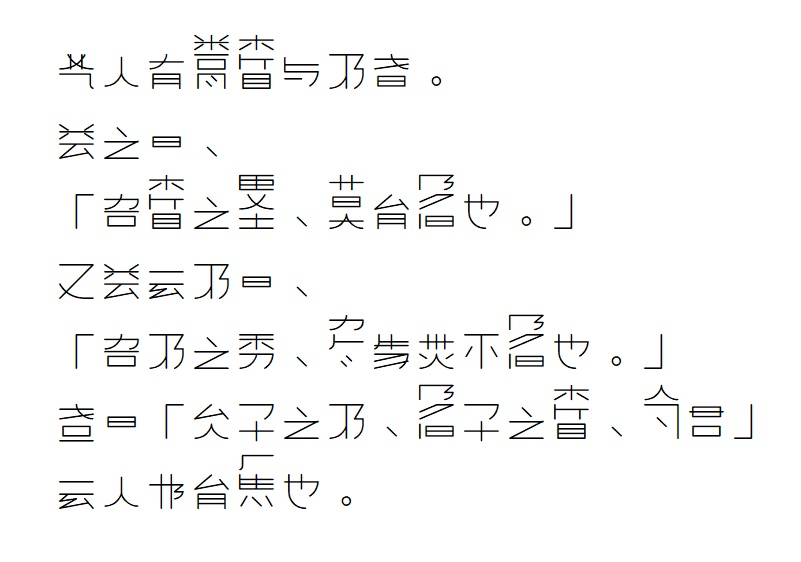
妄想字根打字機(中文字体)
这种字体是由长野利平于 1980 年左右研究出来的。 该字体基于对被称为 “流書”的打字机字符的重新研究。 https://note.com/zoji_numa/n/n92d2d0bfcbe2 他将 88 条用于书写字母的线性线条(称为“字素”) 连接到一台用于欧洲文字书写的打字机上、 他认为,在纸张的顶部、中部和底部敲击这些线条来制作字体是个好主意。 自然,他的研究随着文字处理器的出现而消失了。 ~特点~ 1)将尽可能多的字符(尤其是汉字)统一为上下组合。 2)形状相似的字符尽量组合在一起。 3)从草书起源、流行字、缩写和旧字中组合出新字。 4)如果一个汉字中包含的字符过多,则将其中一些字符截断。 5) 左右上下书写重复的单词,例如“呗”代表“员”,或者 对于不常用的字符,在右下角添加“·”。 汉字包括:平假名、片假名、算术数字、大写字母 A-Z、注音字母、 最小符号、GB 2312的1级汉字等等。 可用于商业用途(风险自负);禁止反社会使用。